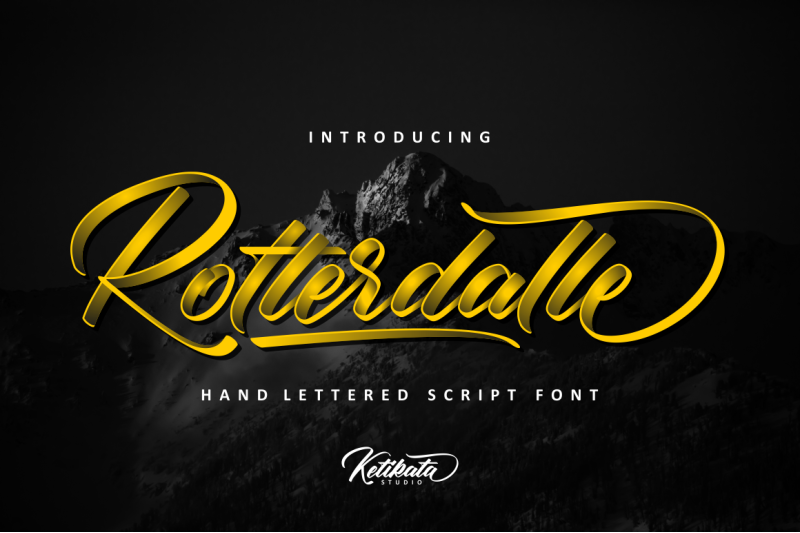
Rotterdalle Script Font – Fonte Grátis
Rotterdalle Script Font
Descubra a elegância do Rotterdalle Script Font, uma fonte script cuidadosamente projetada pela 24Design. Inspirada no estilo delicado e sofisticado dos desenhos à mão livre, esta fonte oferece um toque pessoal perfeito para seus trabalhos de design gráfico. Ideal tanto para criação de logotipos, etiquetas de nome, frases inspiradoras e cartões de visitas quanto para estampar roupas ou embalagens, o Rotterdalle Script destaca-se pela sua conexão elegante entre os caracteres. Criada a partir de um esboço cuidadosamente pensado, essa fonte traz uma sensação jovial e vivacidade aos projetos. Com seus traços finos e detalhes aguçados, o Rotterdalle Script é perfeito para aqueles que buscam uma combinação única e poderosa de sofisticação e personalização. Este é um recurso valioso tanto para profissionais de design como para designers amadores, pois proporciona flexibilidade ao permitir alternativas para conectar os caracteres com precisão e elegância. Seja qual seja o seu projeto, adquira já a sua fonte Rotterdalle Script e transforme suas ideias em realidade, dando um toque personalizado e sofisticado às suas criações.